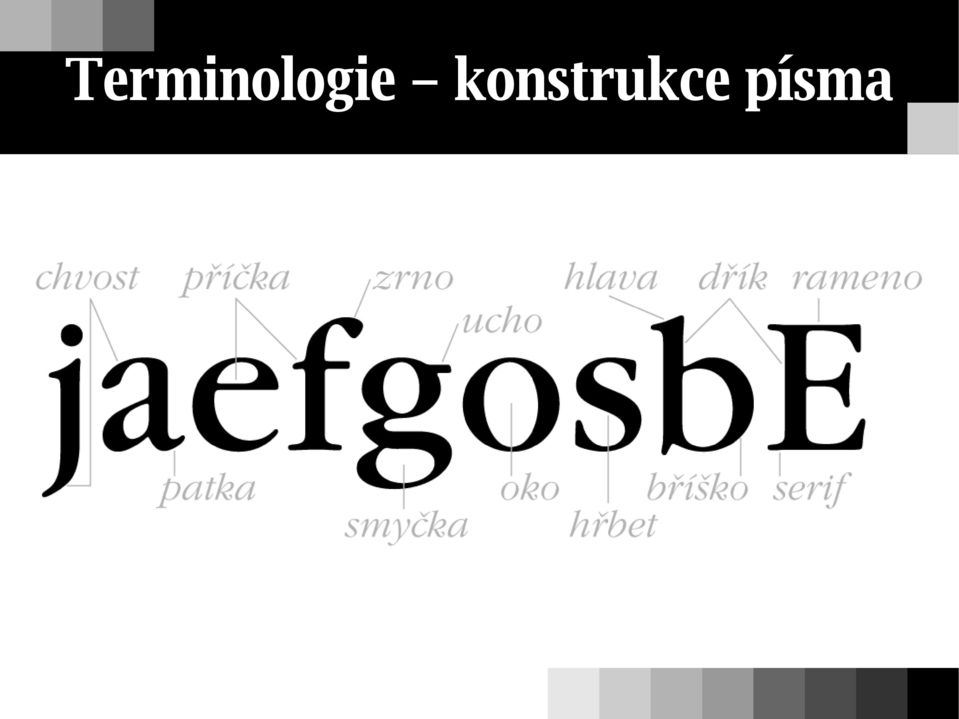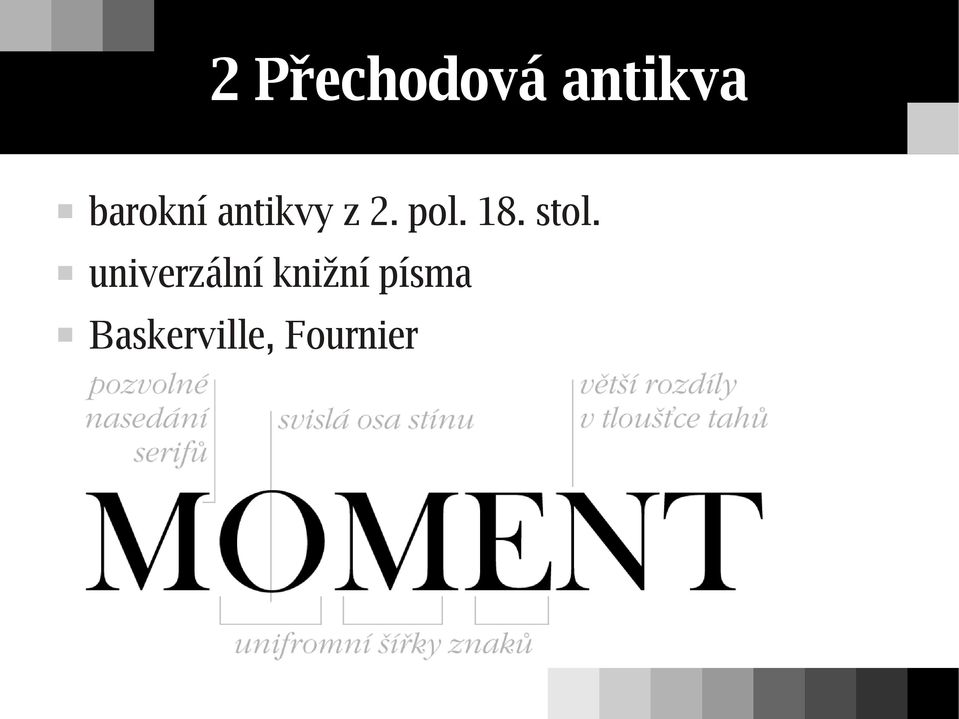
Základní pojmy. sazba: uspořádání textu (a dalších prvků) do stránek typografie: estetická úprava sazby
3 Základní pojmy sazba: uspořádání textu (a dalších prvků) do stránek typografie: estetická úprava sazby práce s písmem a prostorem významnou roli má individuální vkus často nejsou striktní pravidla, jen doporučení jejich dodržováním nespácháte příšernost porušením může vzniknout zajímavý výtvor (ale člověk by měl znát pravidla a vědět, proč je porušuje)
4 Dvě morové rány typografie počítače díky Wordu a spol. může dokumenty sázet každý invaze uživatelů bez znalostí a estetického cítění degradace knih a běžných denních textů Internet radikálně zvýšil dostřel nepoučených amatérů barvy, animace a podobné nebezpečné hračky
5 Písmo zápis jazyka pomocí symbolů druhy písma: obrázkové: hieroglyfy slovní (logografické): čínské slabičné (sylabické): japonské (hiragana, katakana) hláskové (alfabetické): většina (latinka, azbuka)
6 Sumerské klínové písmo nejstarší známé písmo 3400 př. n. l. až 100 n. l. řada variant od obrázků až po abstraktní slabičné typicky zapisováno rákosovým nástrojem do hliněných tabulek
7 Egyptské hieroglyfy 3200 př. n. l. až 400 n. l. slovní písmo, později i fonogramy pro hlásky či slabiky
8 Moderní evropská písma Latinka vznikla pro latinu starých Římanů základem římská kapitála (3. stol. př. n. l.) malá písmena se ustálila v 8. stol. (Karel Veliký, karolínské minuskule) Azbuka vychází z Cyrilice (Bulharsko, konec 9. stol.) původně pro staroslověnštinu, dnes slovanské jazyky
9 Římská kapitála původně tesána do kamene, později i psána tvary geometricky konstruovány základ moderních latinkových písem
10 Karolínská minuskula 8. až 12. stol. ve většině Evropy původ nejasný (Francie/Itálie) základ moderního písma
11 Kaligrafie ručně psané písmo a estetická úprava dokumentů
12 Terminologie (1) tradiční a specifická není zcela jednotná, historická oborová norma ON Písmo, písmařství, písmolijectví majuskule, verzálky: VELKÁ písmena minuskule, minusky: malá písmena kapitálky: VERZÁLKY ve velikosti minusek
13 Terminologie (2) řez písma: charakter písma daný tvarovými prvky jeho kresby rodina písma: soubor písem konzistentního řezu, obsahuje základní písmo a několik vyznačovacích vyznačovací písmo: písmo pro odlišení či zvýraznění části textu kurzíva: skloněné vyznačovací písmo s odlišnou kresbou
14 Část rodiny Garamond
15 Terminologie konstrukce písma
16 Písmová osnova
17 Klasifikace písma závisí na typografické tradici zjednodušeně: antikvy (serifová písma) grotesky (bezserifová písma) neproporcionální písma (jako psací stroj) ozdobná písma česká typografie: detailní členění do 11 skupin
18 1 Dynamická antikva renesanční antikvy 2. pol. 15. stol. až 1. pol. 18. stol. knižní písma Garamond, Centaur, Times New Roman
19 2 Přechodová antikva barokní antikvy z 2. pol. 18. stol. univerzální knižní písma Baskerville, Fournier
20 3 Statická antikva klasicistní antikvy z přelomu 18. a 19. stol. knižní písma Bodoni, Didot
21 4 Lineární serifové egyptienky 19. stol. akcidenční písma Beton, Serifa, Clarendon
22 5 Lineární bezserifové statické grotesky 19. stol. akcidenční a časopisecká písma Helvetica, Folio, Univers
23 6 Lineární bezserifové geometrické ovlivněno konstruktivismem zač. 20. stol. akcidenční písma Avant Garde, Futura (kruh), Eurostil (obdélník)
24 7 Lineární bezserifové dynamické grotesky navazující na renesanční antikvy akcidenční a časopisecká písma Antique Olive, Gill Sans
25 8 Lineární antikva mísí znaky antikvy a grotesku malé serify či jen jejich náznaky akcidenční písma Copperplate, Friz Quadrata, Optima
26 9 Kaligrafické vycházejí z kaligrafických skriptů výrazně diferencované tloušťky tahů akcidenční písma Zapf Chancery, Commencial Script
27 10 Volně psané vycházejí z rukopisných předloh malé rozdíly v tloušťce tahů akcidenční písma Fiesta, Brody, Time Script
28 11 Lomené písma lomených tahů gotického charakteru velmi špatně čitelná akcidenční písma Fette Fraktur, Cloister